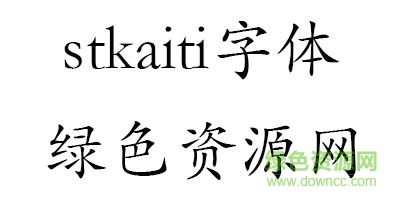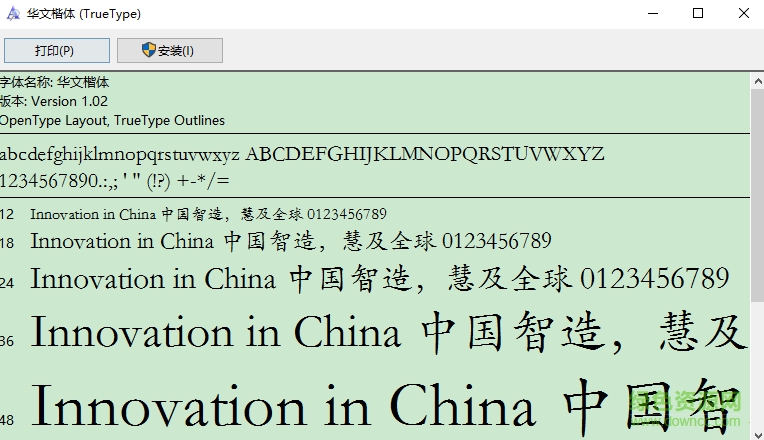
stkaiti字體也就是華文楷體字體,這款字體大氣沉穩(wěn),筆鋒細(xì)膩,整體效果非常出色,喜歡這款字體的朋友歡迎來綠色資源網(wǎng)免費(fèi)下載使用!
華文楷體(stkaiti)是微軟發(fā)布的一套新的字體。隨微軟office軟件發(fā)布。中文字形使用原來的字體(中易楷體),英文部分使用Garamond,數(shù)字也使用Garamond。在Microsoft Office中,可以用字形修整功能。華文楷體字體與word 楷體、楷體-GB2312從外觀看,三種字體有些相似,但在具體的字高字寬比例、字大小、字默認(rèn)行間距等方面有細(xì)微的差別的。